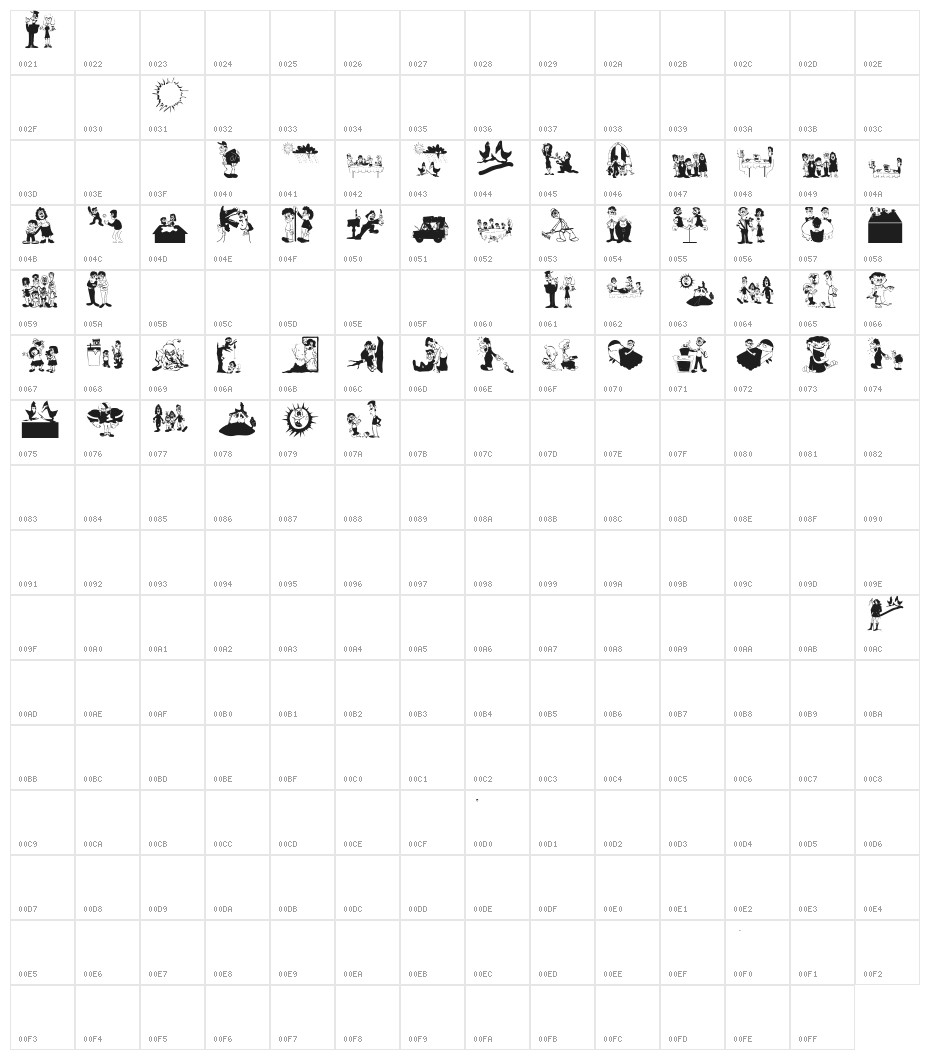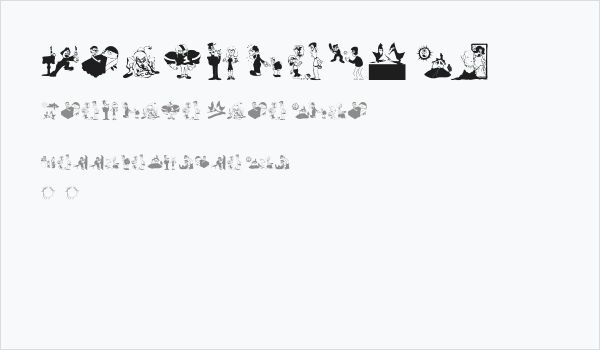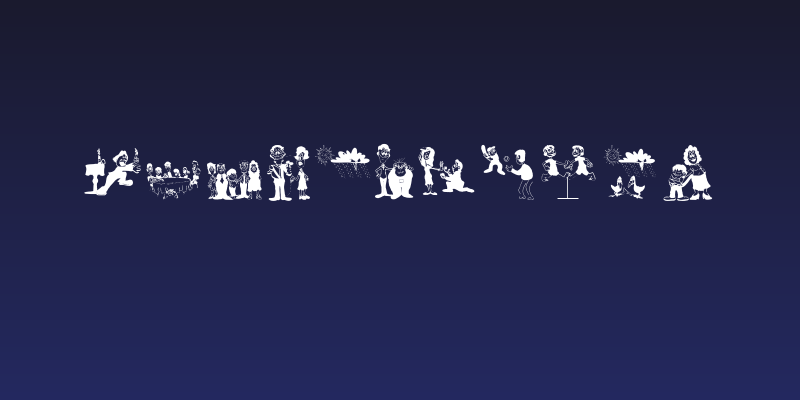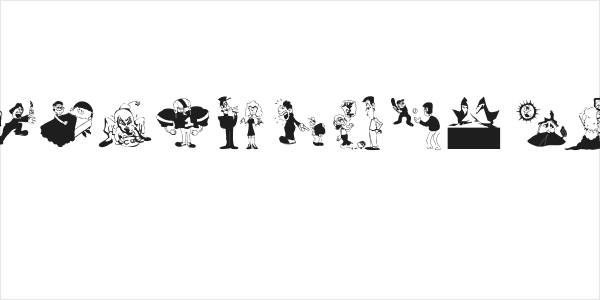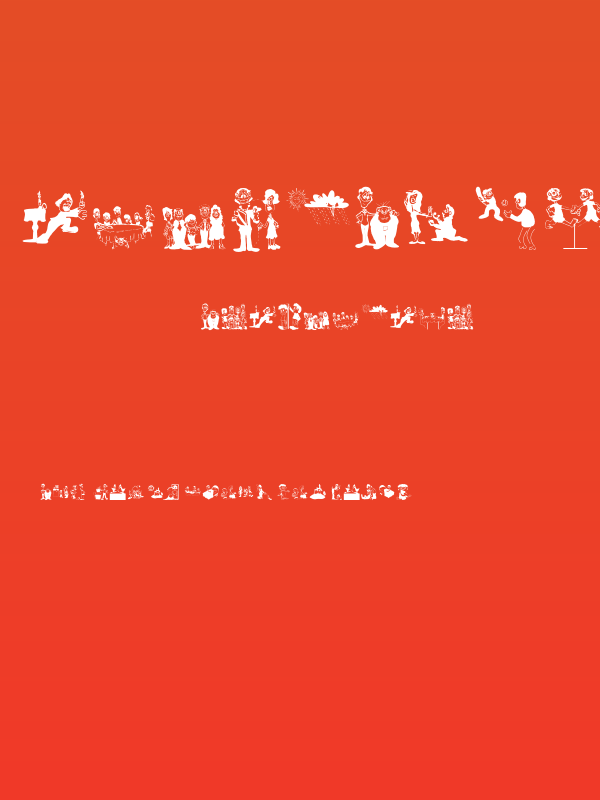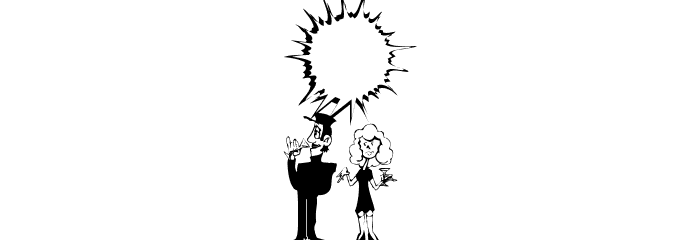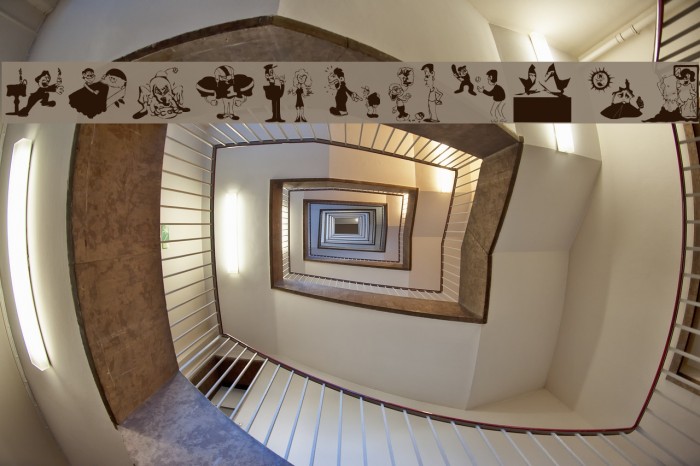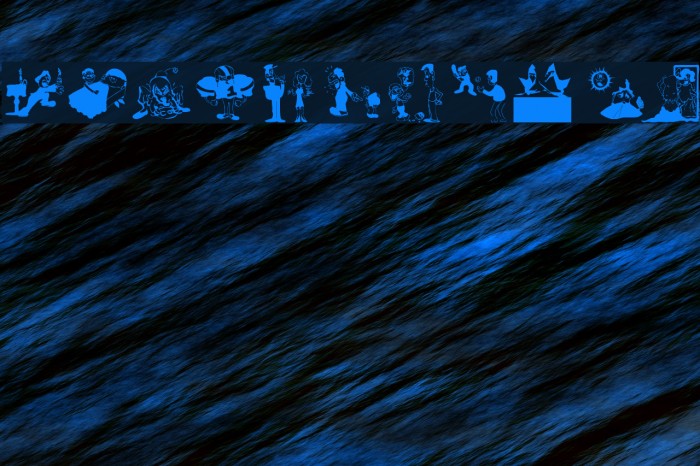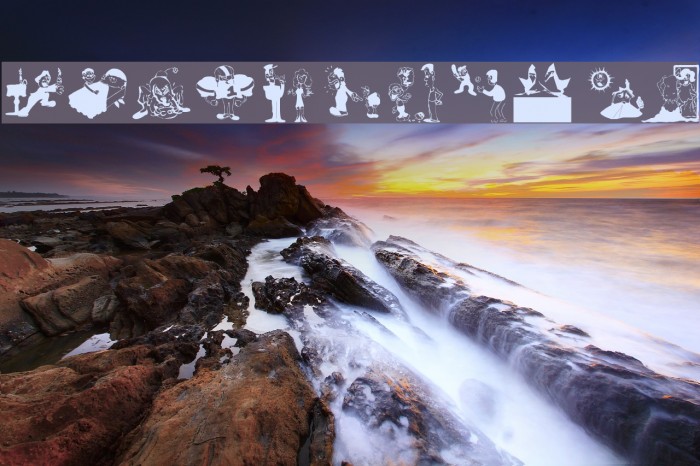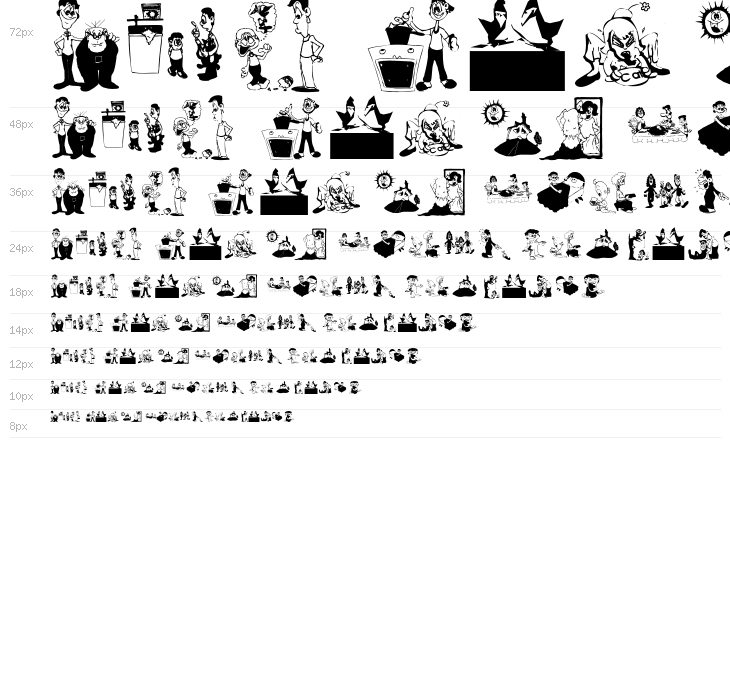
PrivateLuck Font
| Stile generale | Playful, Whimsical, Comic |
| Caso d'uso | Decorative elements, Themed graphics, Titles, Posters |
| Progetti proposti | Party invitations, comic books, educational materials, greeting cards, playful branding. |